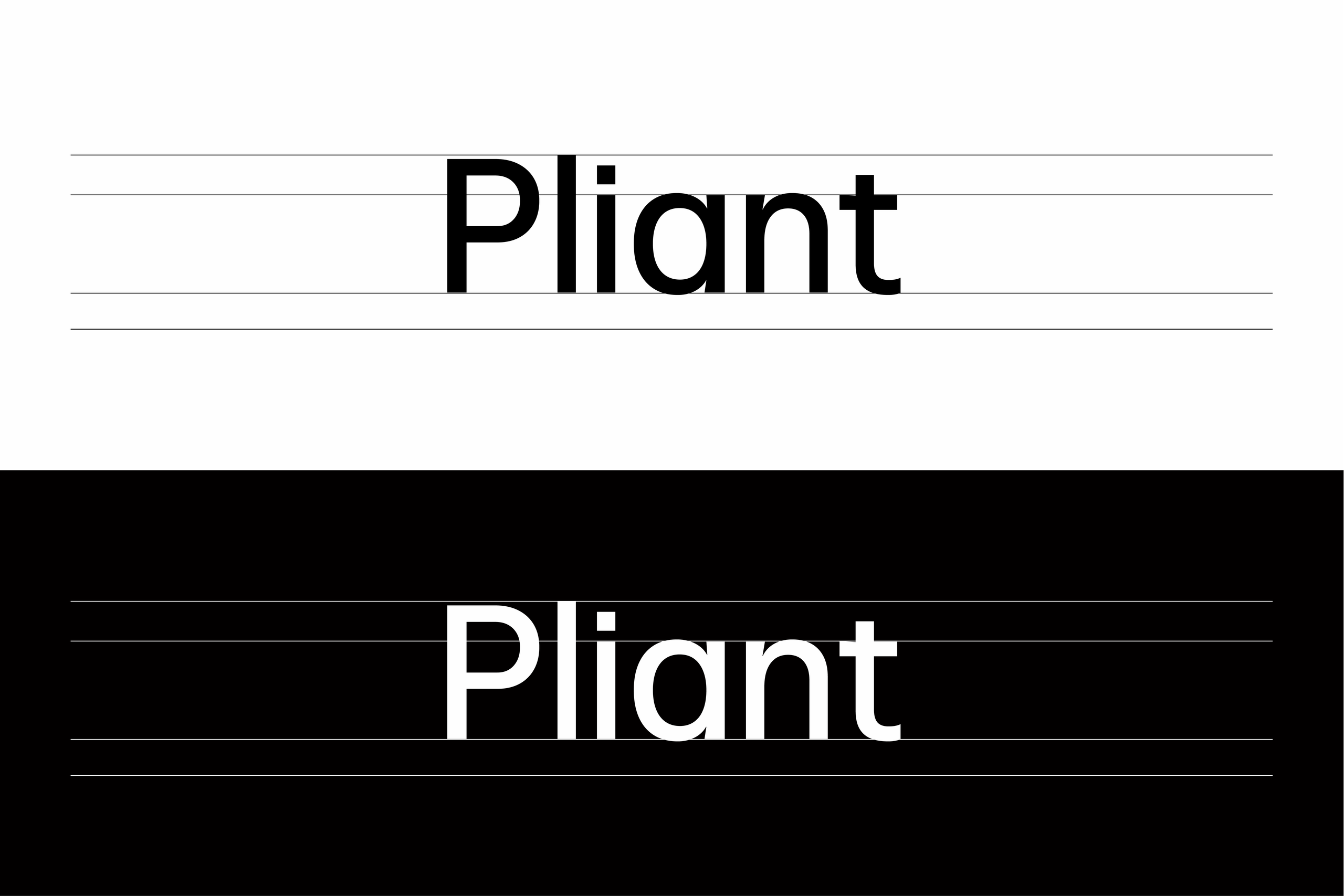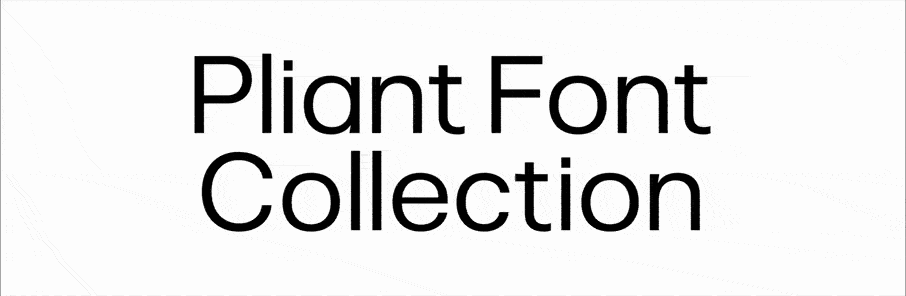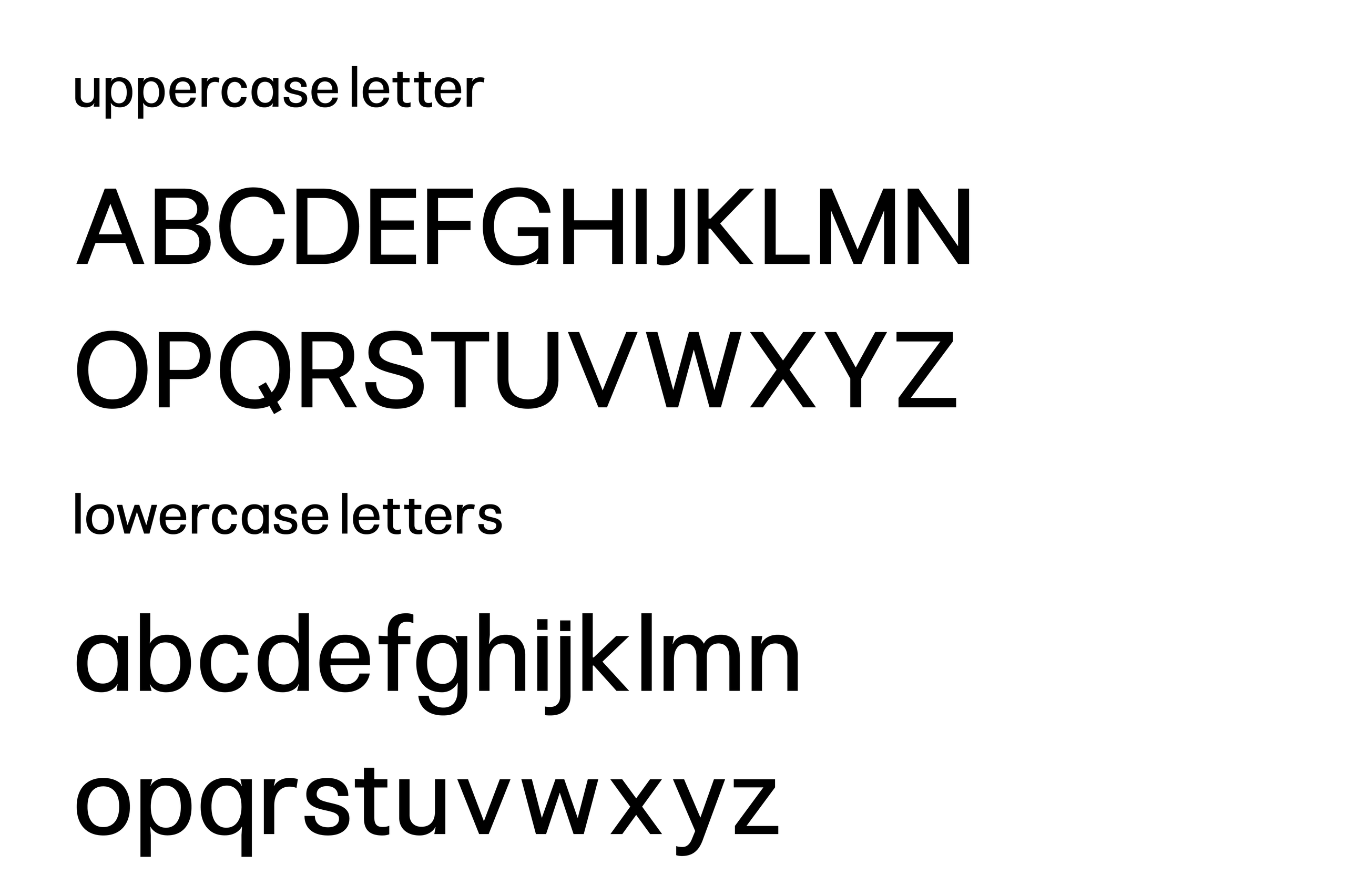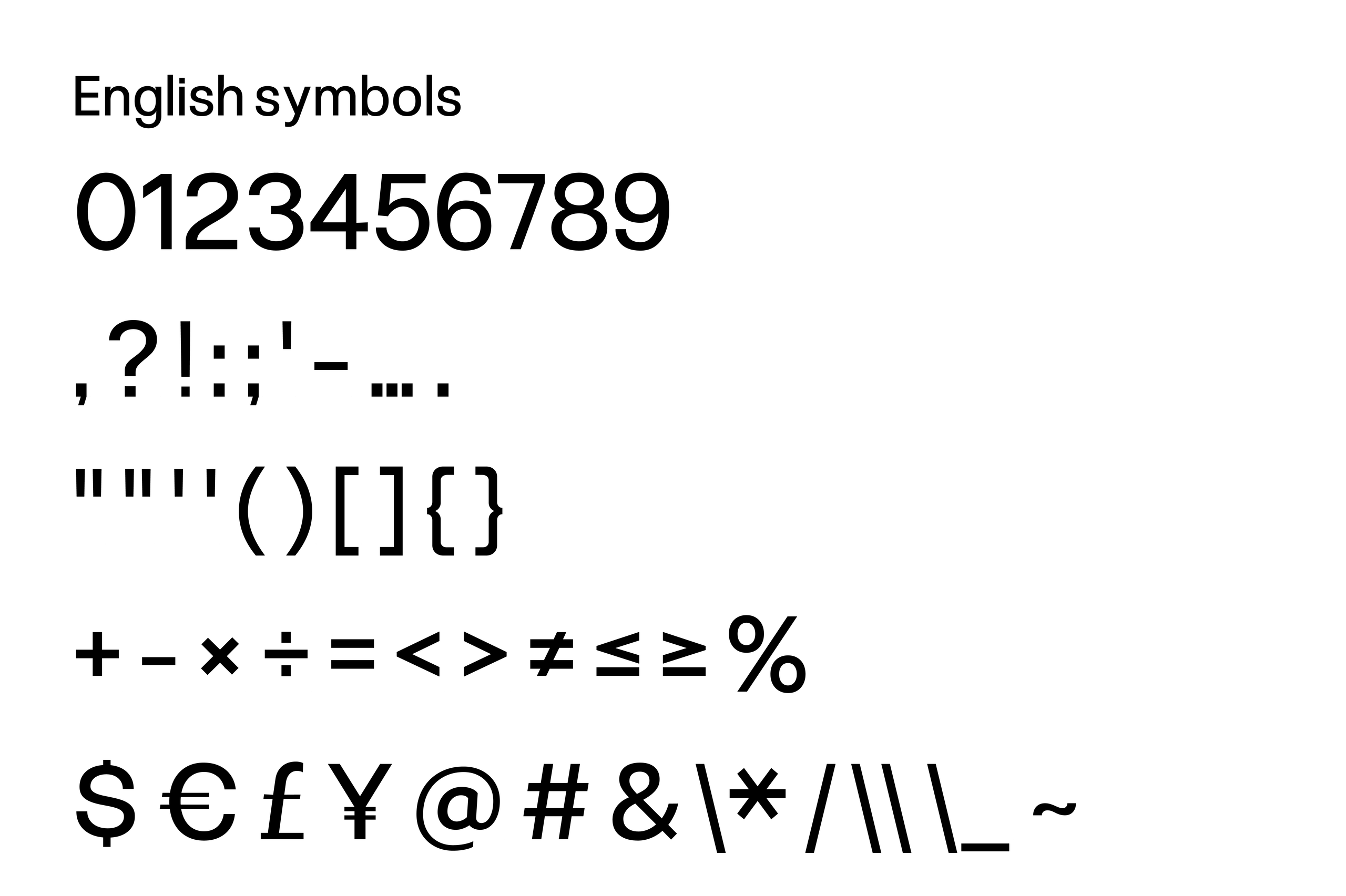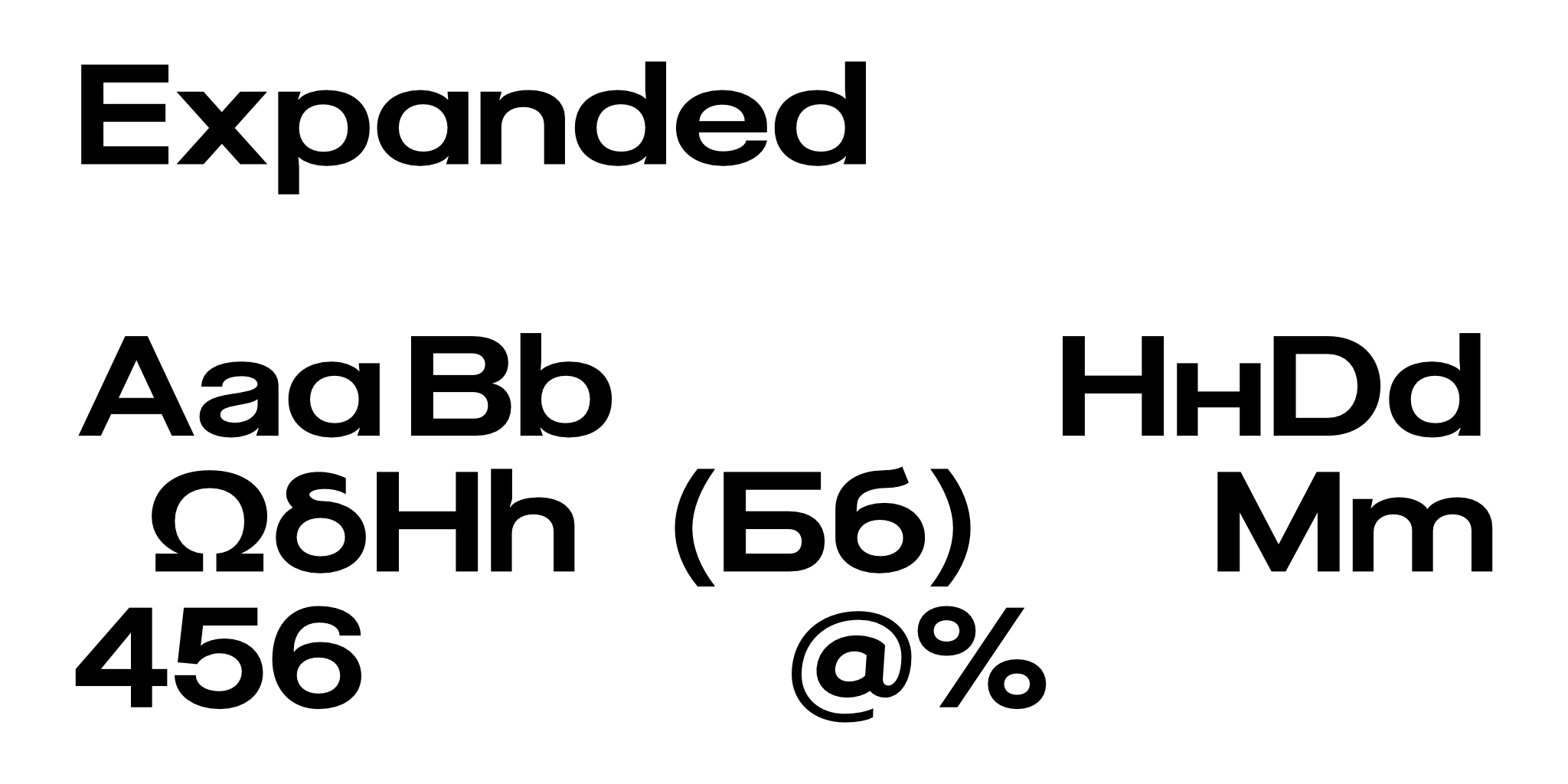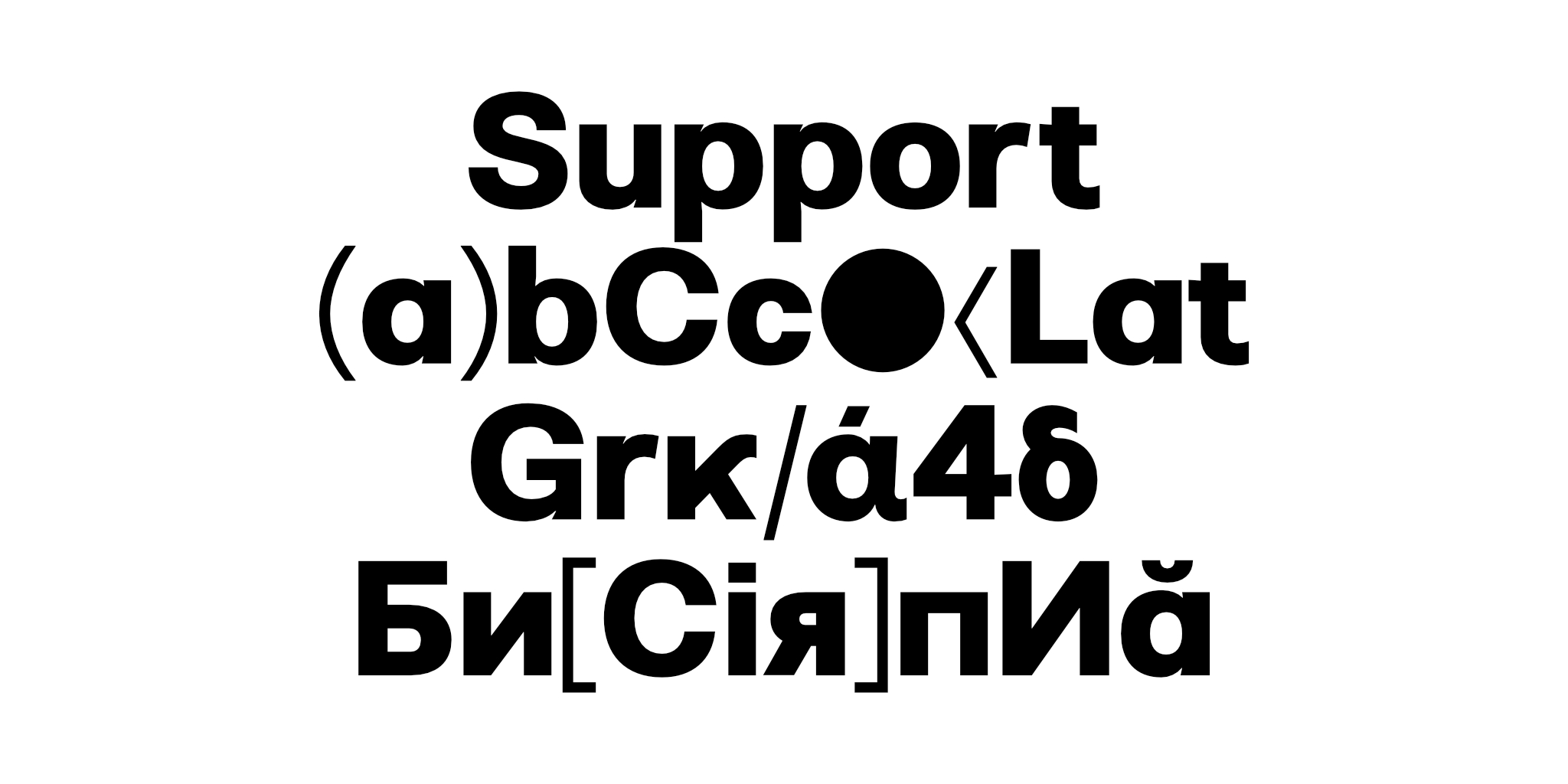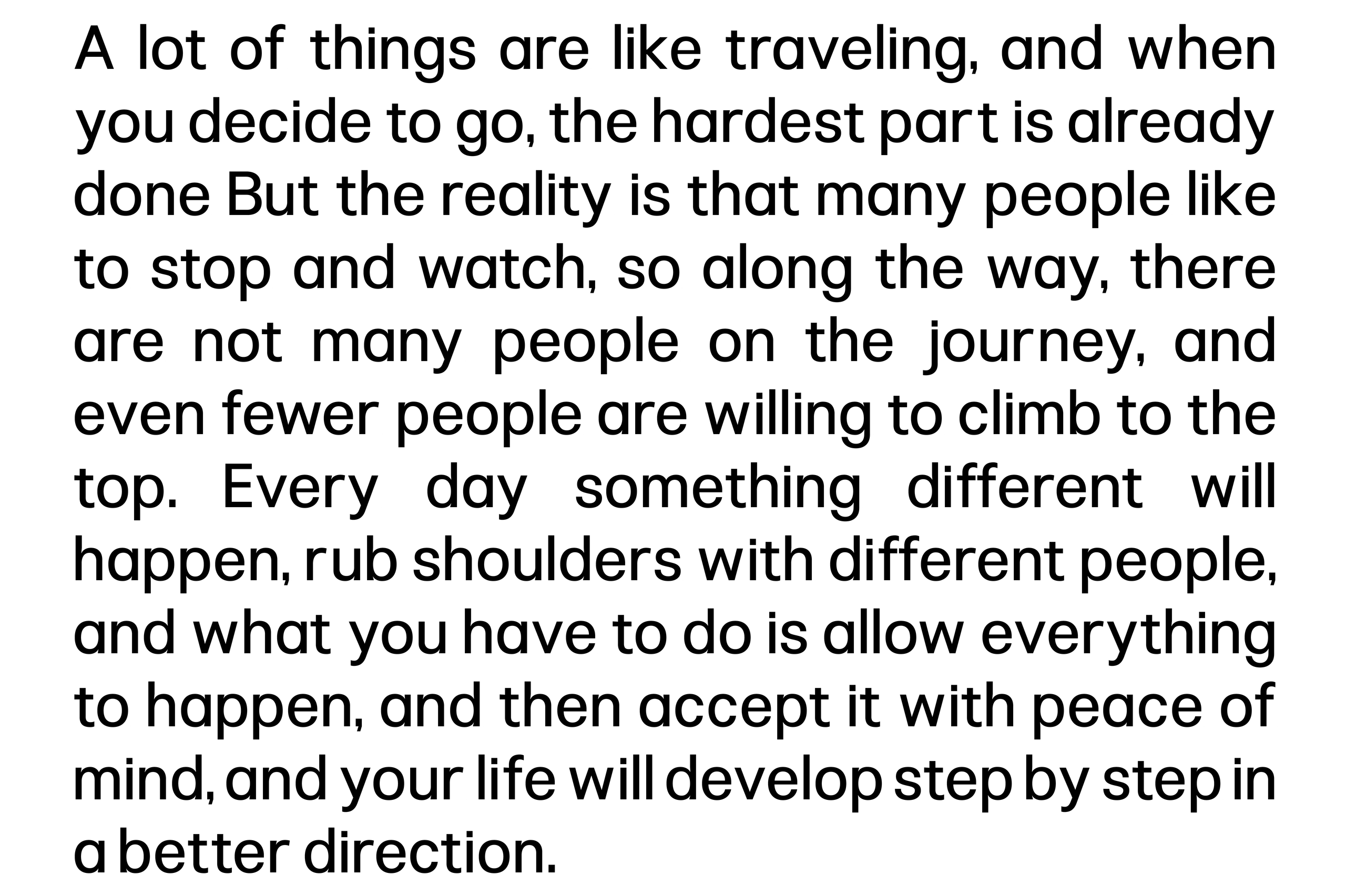
Pliant
Pliant 是一款强调灵活性的现代无衬线字体,由墨西哥蒙特雷的独立字体厂牌 Non Foundry 制作。字体没有刻意加入复杂的装饰,而是从字形比例、笔画结构以及文字空间关系出发,建立了一套简洁而具有变化空间的字体系统,适用于编辑排版、品牌设计、海报以及数字界面等多种设计场景。
从整体字形来看,Pliant 具有比较鲜明的现代无衬线特征。字母结构简洁,笔画粗细关系清晰,圆形字母与直线结构之间保持着较为协调的比例。大写字母视觉上规整利落,小写字母则更加自然,在保持良好识别度的同时,也让整套字体拥有一种干净、理性的视觉气质。
Pliant 最具特色的地方,在于它并不是固定在某一种字宽和字重上的字体,而是将字重与字宽变化融入了可变字体系统之中。通过 wght 和 wdth 两个可变轴,可以在不同程度的字重与宽度之间进行调整,让同一套字体根据版面需求呈现出更加紧凑或舒展的状态。
这种变化在标题设计中尤其明显。当版面空间比较有限时,可以通过缩窄字宽让文字更加紧凑;而在海报标题、品牌视觉等需要更强横向延展感的场景中,则可以使用更加宽阔的字形。字体因此能够在不同尺寸和版式中保持统一的设计语言,同时提供更大的排版调整空间。
除了正体之外,Pliant 还提供斜体样式,使字体在强调文字、标题层级以及动态排版中拥有更多变化。结合可变字重和字宽,设计师可以根据具体内容调整文字的视觉重量与占用空间,而不需要频繁更换不同字体。
在字符支持方面,Pliant 并不局限于英文使用,同时支持拉丁、希腊和西里尔文字,整套字体包含超过 1020 个字形。除了基本的大小写字母、数字和标点之外,还提供标准连字、可选连字、替代字形、分子、分母、上标、下标以及分数等字符与 OpenType 功能,能够满足较为完整的西文排版需求。
Pliant 的视觉表现也比较适合现代设计环境。简洁的字形结构能够很好地融入品牌识别系统,在 Logo 辅助文字、品牌标题和宣传语中保持清晰而统一的效果;用于海报、杂志、网页标题时,可变字宽又能够帮助设计师控制文字与版面的比例。在 UI 设计中,其规整的无衬线结构同样适合导航、按钮、标题以及信息文字等场景。
从设计思路来看,Pliant 更像是一套围绕“适应性”建立起来的字体系统。它并没有依靠夸张的造型来制造个性,而是通过字宽、字重和字形比例之间的变化,让字体能够适应不同的设计环境。尤其是在需要统一字体风格、同时又希望文字在不同版面中保持变化的项目中,这种设计方式具有较大的使用空间。